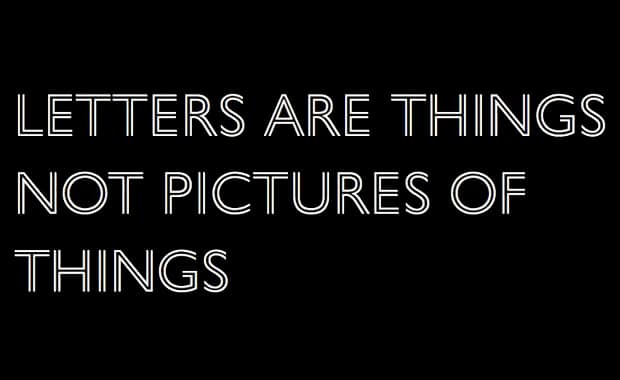
Neuauflage: Monotype stellt Eric-Gill-Serie mit 77 Fonts vor
Die originale Gill Sans prägte die Kulturwelt visuell über Jahrzehnte und fand zuletzt Verwendung in populären Filmtiteln wie „Toy Story“ und „Findet Nemo“ sowie in den Markenidentitäten von BBC, British Railways und Penguin Books.
Die vier Monotype Schriftdesigner Steve Matteson, George Ryan, Ben Jones und Terrance Weinzierl arbeiteten aus verschiedenen Teilen der Welt an der Eric Gill-Serie, um Gills Arbeiten für das 21. Jahrhundert neu zu beleben und sein Schaffen sowohl für digitale Kommunikationsmittel als auch für anspruchsvolle Print-Anwendungen fit zu machen.
Dank Original-Zeichnungen und -Material aus Gills Hinterlassenschaft, aufbewahrt in Monotypes historischem Archiv, sind viele Neuerungen von Gill selbst vorbereitet. Teil der Serie ist außerdem eine völlig neue, von Gill inspirierte Schrift des Monotype Designers Terrance Weinzierl, die speziell für den Einsatz und die Lesbarkeit in digitalen Umgebungen entwickelt wurde. Joanna Sans Nova setzt als Sans-Version mit einem frischen Look-and-Feel die humanistische Tradition der Joanna fort.
Die Schriften der Eric-Gill-Serie:
Gill Sans Nova
- Designer: George Ryan, Monotype
- Anzahl der Schriftschnitte: 43 (gegenüber 18 in der Original Gill Sans) – von Ultra Light bis Ultra Bold, zusätzlich eine komplette Serie an Condensed-Schnitten
- Neue Display-Schriftschnitte: Sechs Inline-Schnitte sowie schattierte Outline-Schriften, inspiriert vom nie digitalisierten Original-Design und von der Gill Sans Nova Deco-Schrift, die einst aus der Monotype-Schriftbibliothek entfernt wurde
- Sprachunterstützung: Lateinische Sprachen (nur für Display-Schriftschnitte), Griechisch und Kyrillisch
- OpenType-Features mit „typografischen Leckereien“ sowie für Stilvarianten aus verschiedenen Phasen der Sans-Historie
Joanna Nova
- Designer: Ben Jones, Monotype
- Anzahl der Schriftschnitte: 18 (gegenüber 6 in der Original Joanna) – von Thin bis Ultra Black
- Sprachunterstützung: Lateinische Sprachen, Griechisch und Kyrillisch
- OpenType-Features für typografische Feinarbeiten, einschließlich Kapitälchen, diverse Ziffernarten und kontextbedingte Ligaturen
Joanna Sans Nova
- Designer: Terrance Weinzierl, Monotype
- Anzahl der Schriftschnitte: 16 – von Thin bis Black
- Sprachunterstützung: Lateinische Sprachen, Griechisch und Kyrillisch
- OpenType-Features für anspruchsvolle Typografie, einschließlich Kapitälchen, diverse Ziffernarten und Ligaturen